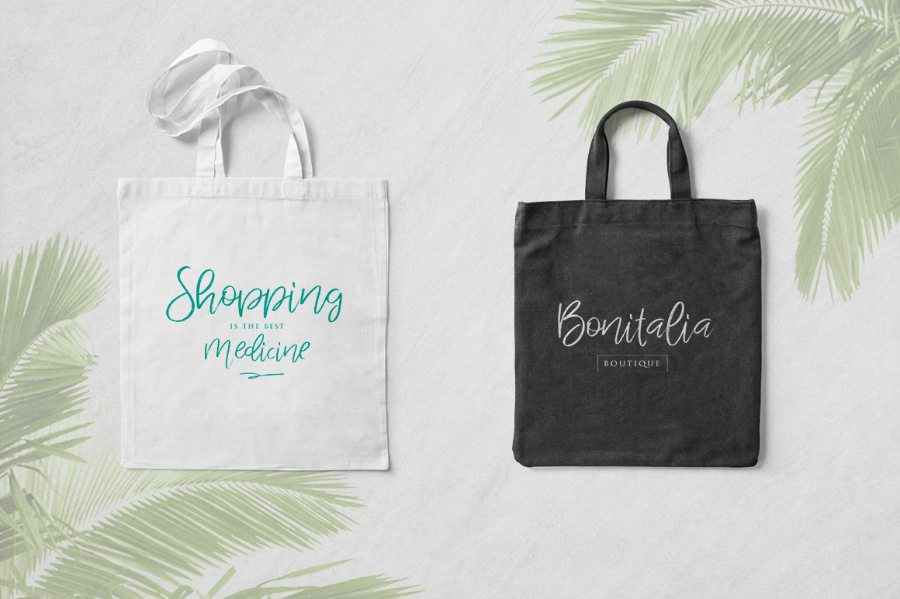
Jandys脚本免费演示
Jandys Script Free Demo是由Alit Design提供的免费版Jandys 脚本。这种干刷和优雅的风格字体看起来很自然,就像真正的手写。这种字体将是理想的任何设计项目与优雅,酷和乐趣的概念。 Jandys脚本也很适合标识,网站标题,T恤设计和婚礼邀请。